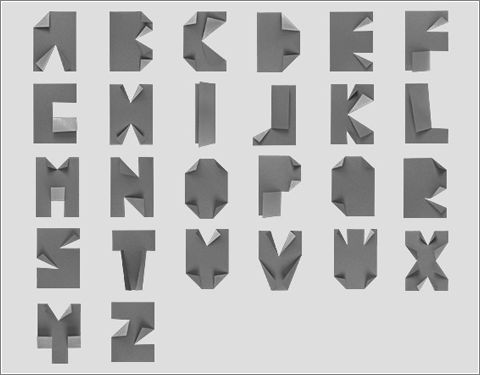
Una tipografía hecha de hojas de papel
Hand-Mande-Font-A4
A4 es una simpatiquísima tipografía de Hand Made Font, unos diseñadores estonios. Cada letra está construida mediante cortes y plegados en una hoja de papel de tamaño A4.